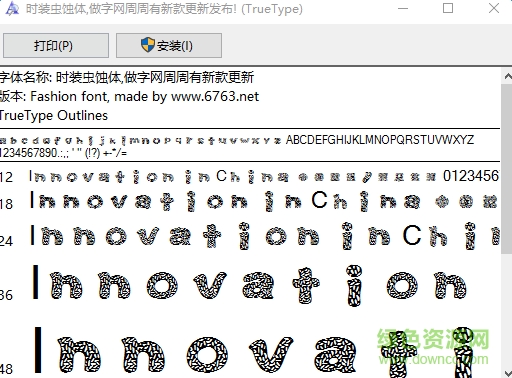
時(shí)裝蟲(chóng)蝕體
時(shí)裝蟲(chóng)蝕體是時(shí)裝字庫(kù)中的很有特色的一款電腦字體,這款字體最大的特色就是它寫出來(lái)的字不是實(shí)心的,就像被小蟲(chóng)子啃食過(guò)一樣都是圓洞,這也是它的魅力之處,喜歡的朋友可以來(lái)綠色資源網(wǎng)下載。